家名制作例「井上家」
家名制作例
・どんな家系ですか?
代々独立心の強いものが多く、海外で活躍するものもあり、言葉は強いがは家族思いであるところが自慢の家系です。
どのような内容でも、お伝えいただいたイメージに沿って、心を込めて筆耕いたします。
遺された人が立ち寄れる場所を
墓前に立つとき、私たちは亡き人と向き合っているようで、
本当はいまを生きる自分自身と向き合っているのかもしれません。
雑草を抜き、箒ではき、綺麗になったお墓で香をたく
飾った花の向こうに故人との思い出がよぎる
ささいな日常でのこと、ふとした時にかけてくれた言葉、
困った時にかけてくれた言葉。
いつも守ってくれてありがとう
たまに、間違えたら教えてねと思います。
春分のお彼岸、これから陽気を受けてはばたく時
秋分のお彼岸、エネルギーを内に蓄える時
節目に手を合わせて命に向き合う。
そんな場所でもあるかもしれません。
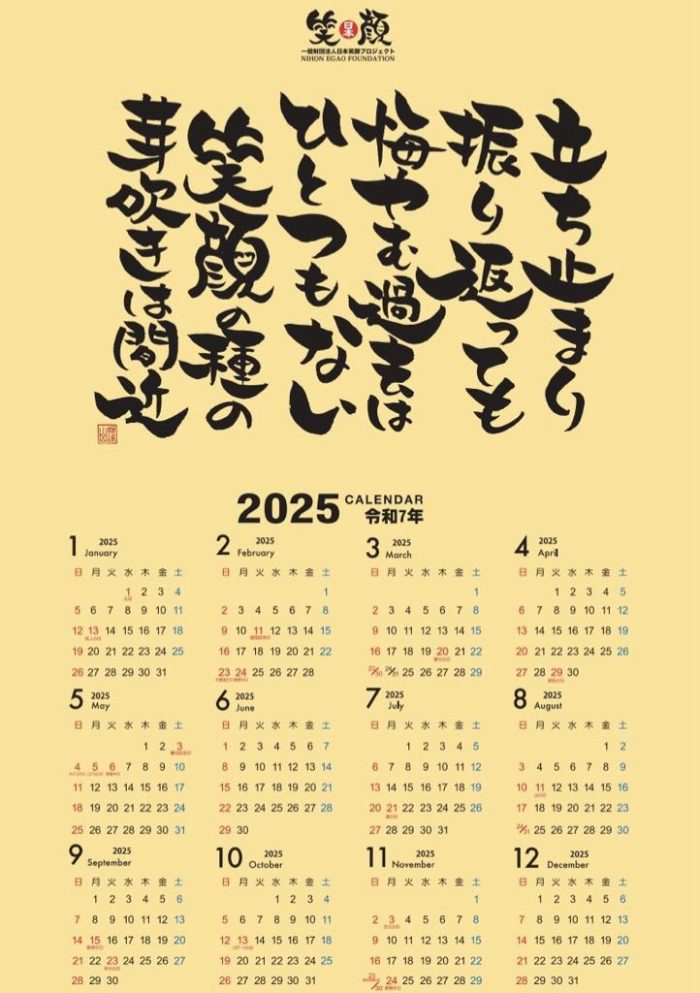
時間の経つのは本当に早いですね。
今年もあとわずかとなりました。
皆さんの1年を振り返り
どうでしたでしょうか。
目標達成できたことまだ途中なこと。
ゆっくりと一年を思い起こしてみてください。
時代の進化がとても早く情報や周りの状況に
飲み込まれしまうケースもたくさんあります。
物事がうまく進まないこともたくさんあります。
時として立ち止まり、過去を振り返り明日からの進むべき道を探す。
その時に重要となるのは、過去を悔やまない
失敗もあります。
ただ、失敗は挑戦できたからこそ
得られる結果で
何も悔やむことは必要ありません。
失敗という結果は必ず、その先の芽吹の肥やしになります。
そうなると、失敗の連続は、
どんどん肥やしが増え豊かな土壌が育っていきます。
土の中なので微生物や栄養は目に見えません。
しかし、種を植えた後にしっかり発芽し、ぐんぐん成長します。
来年2025年の笑顔カレンダーはそんな言葉を添えてみました。
合掌 林映寿
文字を○で囲み・桜のモチーフもあしらって
お墓の文字・偲
墓石文字の書をご提案いたしました。
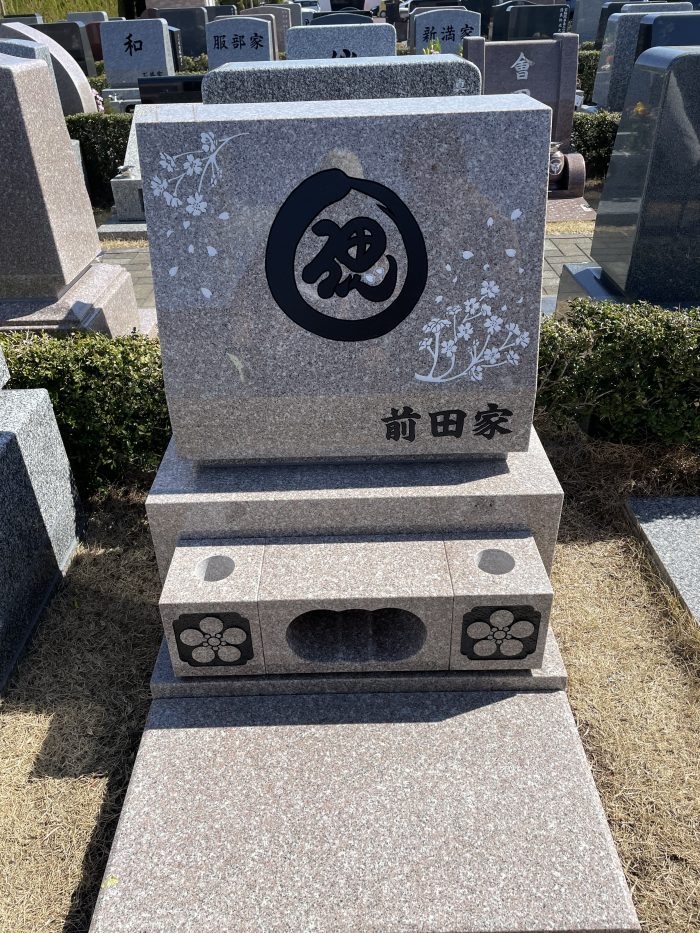
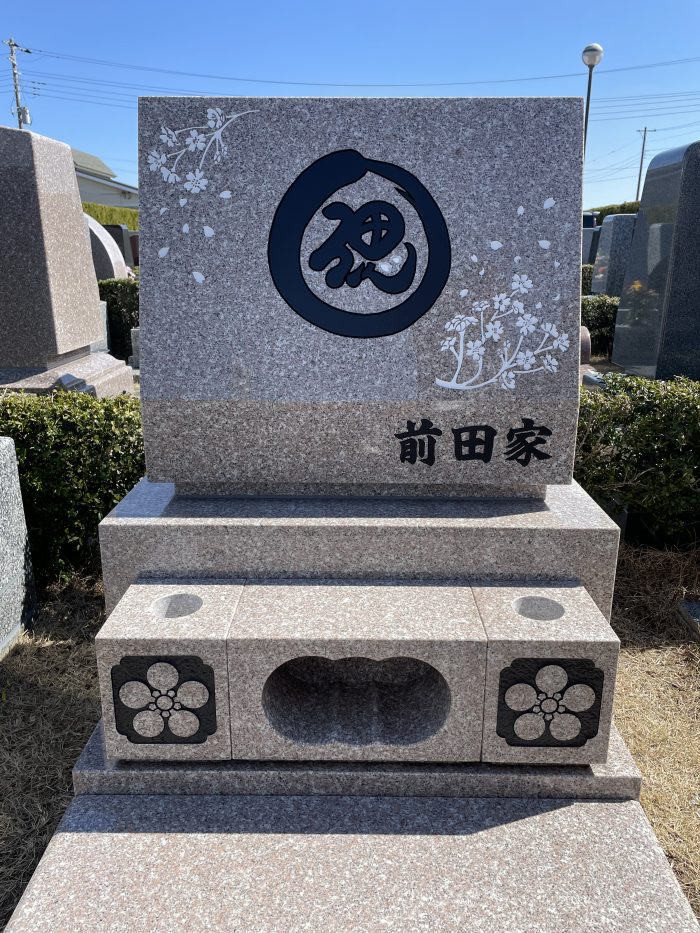
施主M様よりご感想をいただきました。
こんにちは。以前、墓石文字を注文したMです。
昨年、主人が亡くなり、お墓を建てることとなり、
素敵な墓石文字をデザインしていただきまして、ありがとうございます。
遅くなりましたが、先月墓石が完成しまして、
今週末に一周忌法要を執り行うこととなりました。
つきましては、墓石の引き渡しの時に撮った写真をお送りさせて頂きます。
想像通りの素敵なお墓が出来上がり、
家族全員で霊園の方へ参り、確認してまいりました。
ご住職に書いていただいた文字も素晴らしく、
落ち着いた温かみを感じる墓石となり、
家族も大変喜んでおります。亡くなった主人も、
きっと気に入ってくれる事と思います。
M様からは昨年の冬に入ったころご依頼をいただきました。
(メールのみの打ち合わせ)
今回は優しさと柔らかさを表現した書を採用されました。
他には現世との繋がり・包み込むイメージのもの
にんべんを上向きに躍動感を加えたもの合わせて3つ提案。
字を囲む丸も3種類の中からお選びいただき、石材店さんには桜のイラストを入れていただいたようです。
対話をしながら進めていくことができ、ご希望どおりのものが出来上がりました。
ご主人様にも喜んでいただけたなら嬉しい限りです。